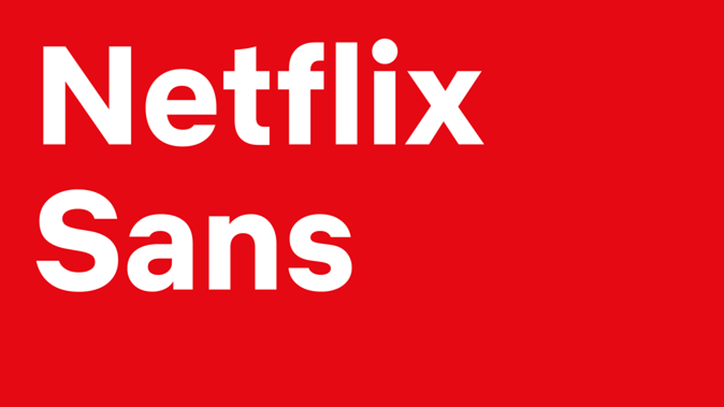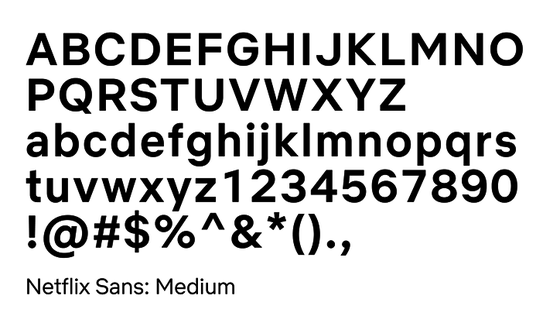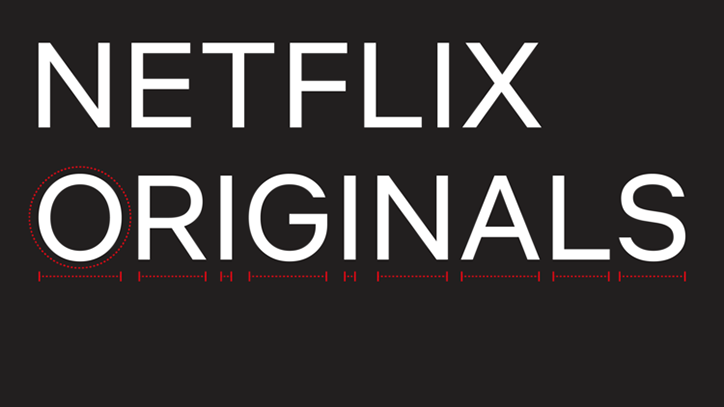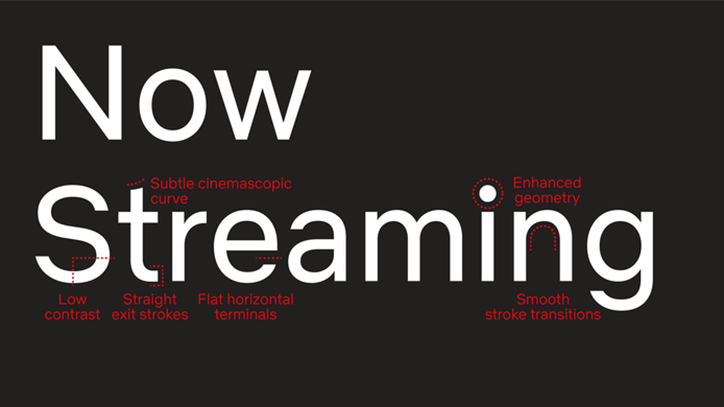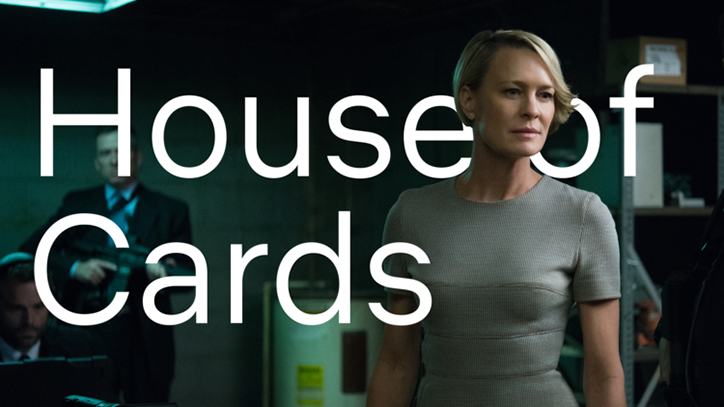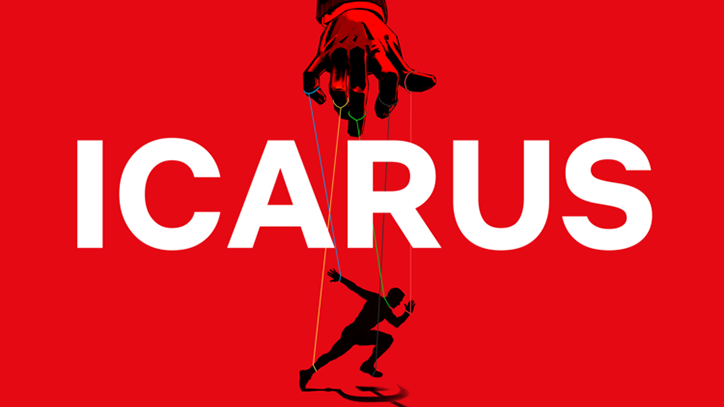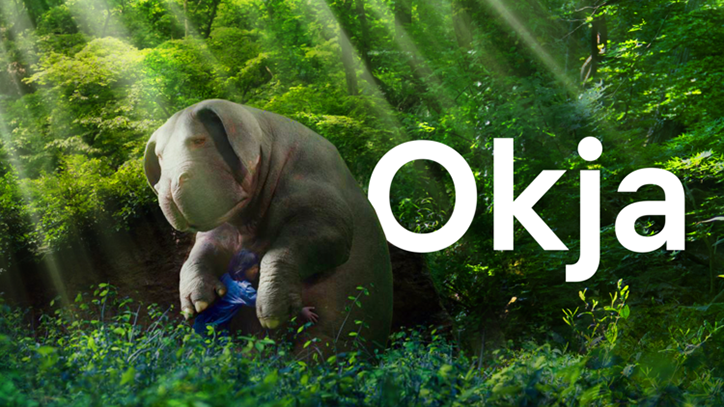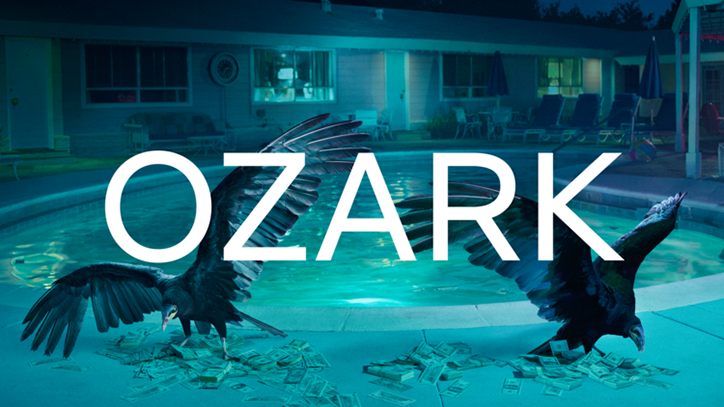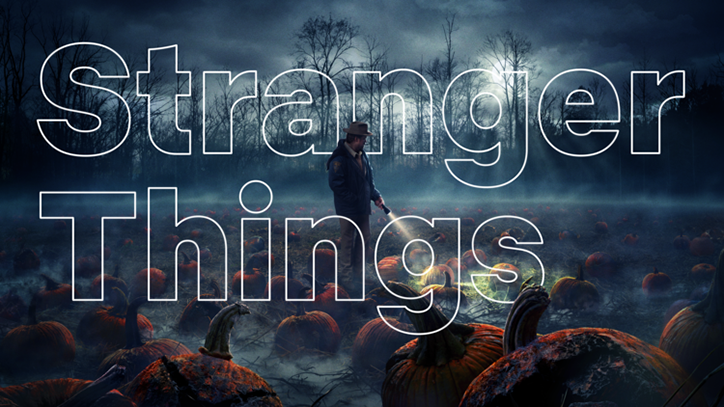
Netflixがオリジナルフォント「Netflix Sans」を開発
世界190ヵ国以上で映像ストリーミング配信サービスを行う「Netflix(ネットフリックス)」がオリジナルのフォント「Netflix Sans」を開発し、今後使用していくとの情報が明らかになった。
Netflixでは、これまで自社サービス及び広告などにフォント・Gothamをメインに使用し、莫大なフォントライセンス料を払い続けてきた経緯があり、そのコストカットとコンテンツエクスクルーシブ性を高めるために「Netflix Sans」というフォントを開発するに至った。
Netflix Sansの特徴
「Netflix Sans」はデザイナー・Dalton MaagとNetflixのデザイン部門を率いるTanya Kumar、Noah Nathanらによって開発されたフォント。
Noah Nathanによると、今回発表した新フォントは「新たなフォントを開発することは我々自身やブランド哲学にさらなる独自性を与えるだけでなく、数百万ドル規模のコスト削減にもつながります」とコメントしている。
また「Netflix Sans」には、「小文字のtの上部分が微妙にシネマスコープな曲線を描いている」「小文字のnの曲線が太さを変化しつつカーブしている」といった特長があり、大文字はより「映画的」、小文字は「コンパクトで効率的」であることをテーマにして、視覚的に鬱陶しくなく、ディスプレイに映えるフォントを目指している。